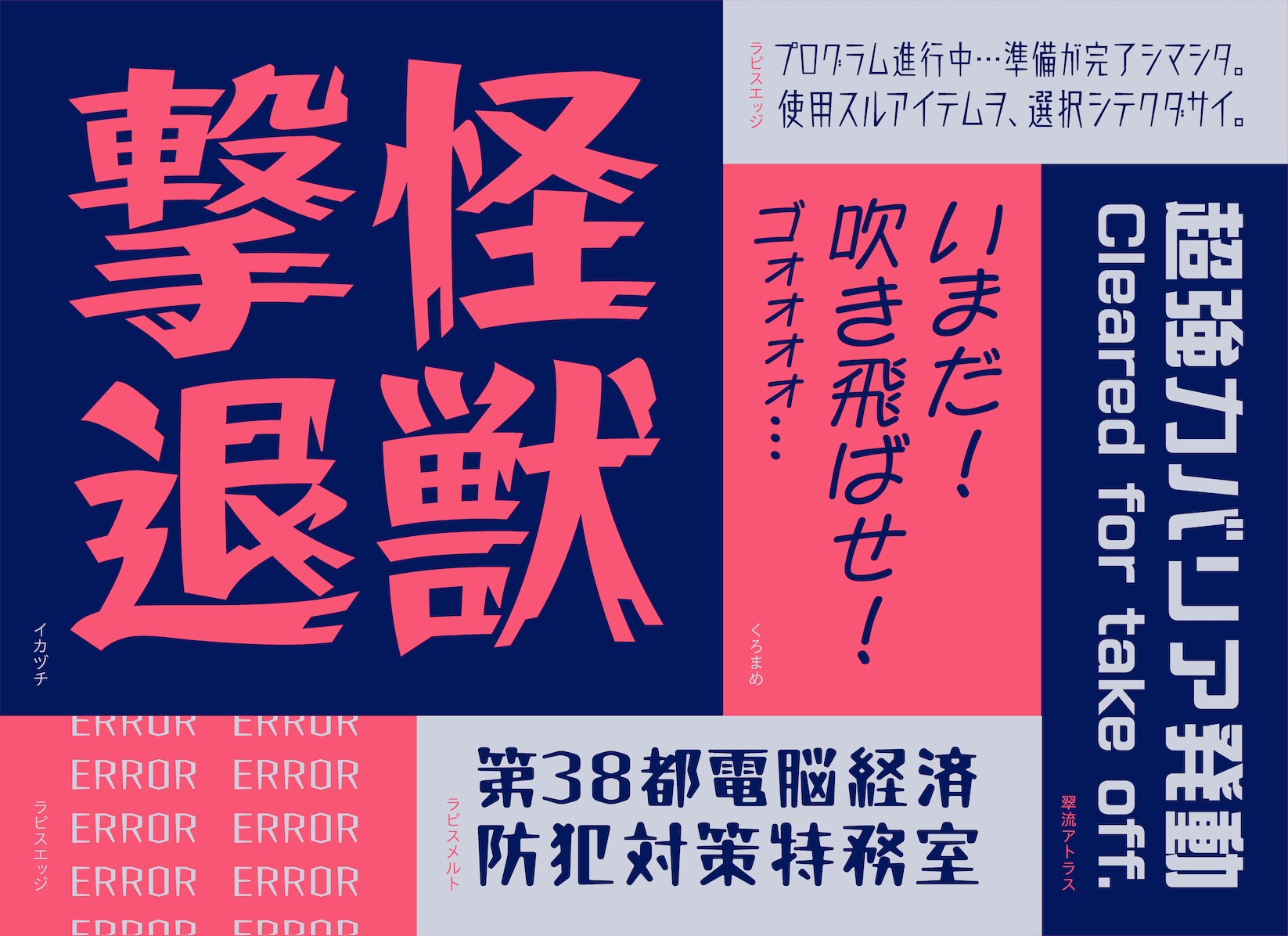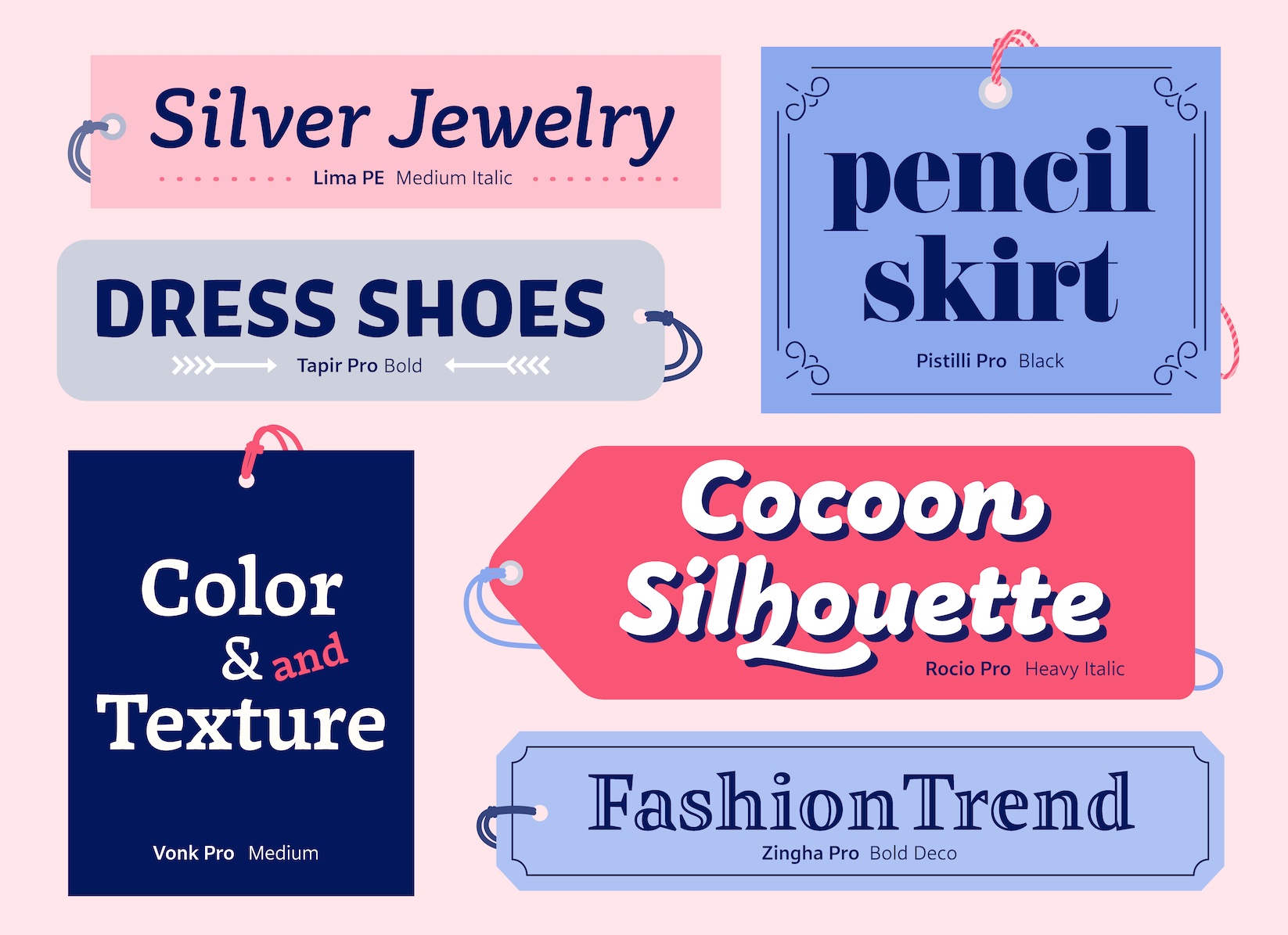
モリサワ、今秋リリース予定の新書体を発表
株式会社モリサワが、2022年秋にリリースする新書体を発表しています。
和文書体は4ジャンル25ファミリー、欧文書体は4ジャンル49ファミリーの計74ファミリーです。
和文書体
インパクト – 字面が大きめで迫力を感じさせる書体
• イカヅチ
• くろまめ
• 翠流アトラス(R/M/B)
• ラピスエッジ、ラピスメルト(L/M/B)
ゆるポップ – あどけなさや遊び心を感じさせる書体
• ココン
• タカ風太
• ちさき
• ぽってり(L/R/M/B)
• プフ ホリデー
• プフ ポッケ
• プフ マーチ
• プフ ピクニック
ロマン – 個性的な装飾を取り入れたレトロ可愛い書体
• オズ
• 白のアリス
• 翠流ネオロマン、翠流デコロマン
オールド – 筆や活字の雰囲気を残したクラシカルな印象の書体
• 霞青藍(L/R/M/B)
• 霞白藤(L/R/M/B)
• 白妙、白妙 オールド(L/M)
• 秀英にじみ四号太かな
• 文游明朝体 古雅かな、文游明朝体S 朝靄かな、文游明朝体S 水面かな
欧文書体
オーガニック&ディスプレイ – 有機的なスタイルや見出し用途の強いインパクトを持つ書体
• Abelha Pro
• Areon Pro
• Concert Pro
• Eminence Pro
• LatinMO Pro、LatinMO Condensed Pro
• Lima PE
• Pistilli Pro
• Rocio Pro
• Tapir Pro
• Vonk Pro
• Zingha Pro
クラシカル&スタンダード – 伝統的なスタイルやシンプルで汎用性の高い書体
• BodoniMO Pro、BodoniMO Condensed Pro
• CaslonMO Pro、CaslonMO Condensed Pro、CaslonMO Compressed Pro
• Cetra Text Pro、Cetra Display Pro
• Letras Oldstyle Pro、Letras Oldstyle Narrow Pro、Letras Oldstyle Condensed Pro
• Pietro Text Pro、Pietro Display Pro
• Prelude Pro、Prelude Condensed Pro、Prelude Compressed Pro
• Star Times Text Pro、Star Times Display Pro
• VibeMO Pro、VibeMO Condensed Pro、VibeMO Compressed Pro
Roleスーパーファミリー – 世界的書体デザイナーのマシュー・カーター氏をメインデザイナーに迎えて開発した書体
• Role Text Serif/Sans/Slab/Soft、Role Display Serif/Sans/Slab/Soft、Role Banner Serif/Sans/Slab/Soft
Clarimo UDシリーズ – 「UD新ゴ」との併記を目的に開発されたサンセリフ体「Clarimo UD PE」のコンデンス書体
• Clarimo UD PE Narrow、Clarimo UD PE Condensed、Clarimo UD PE Extra Condensed、Clarimo UD PE Compressed、Clarimo UD PE Extra Compressed